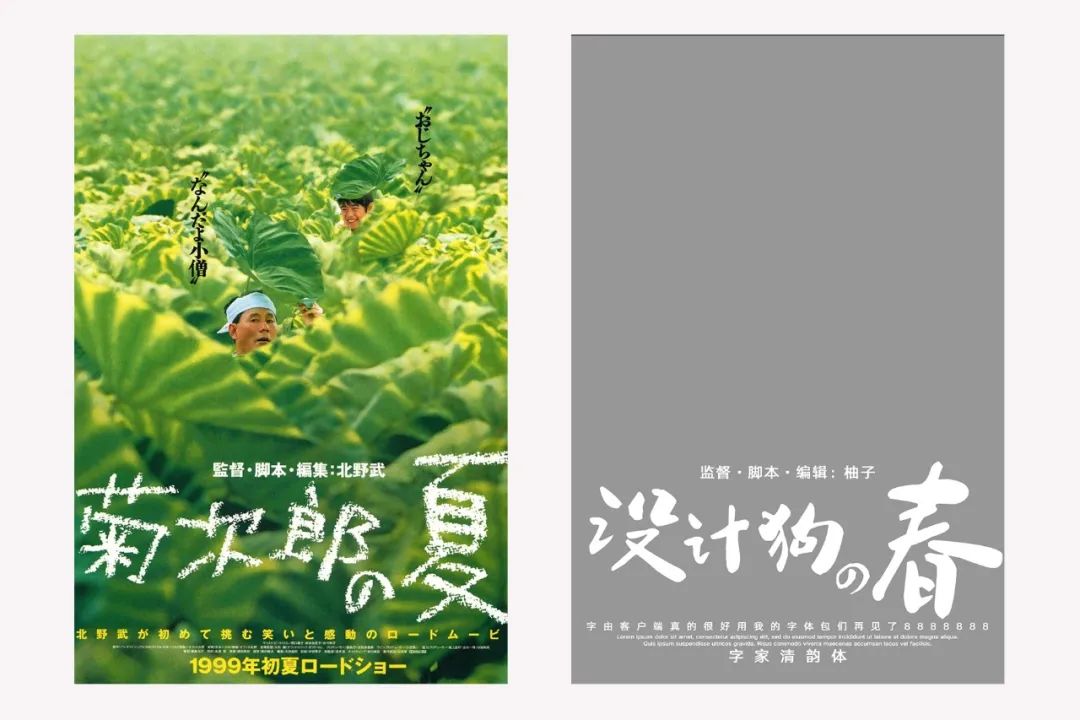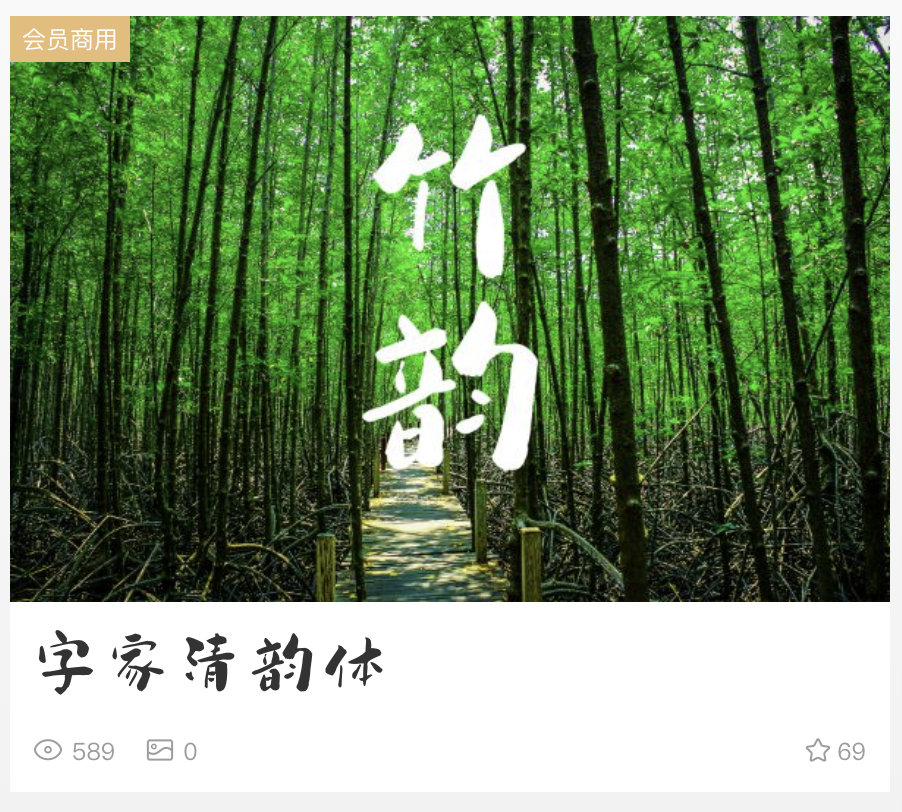
如何在朋友圈不动声色地“撩甲方”,这几招赶紧学起来~
🌱天气慢慢暖和起来了,小伙伴们准备好出游踏青了吗~出门踏青一定要多拍些美美的照片发朋友圈~
作为一名优秀的设计从业者,朋友圈的图片可是对你设计水平的肯定啊!要抓紧机会发财~
万一这样的朋友圈,被挑剔的甲方霸霸看到了,怎么能放心地把设计需求交给你呢?
想脱颖而出的诀窍就是模仿电影海报啊!文艺气质一下就上来了,甲方霸霸看过以后直呼内行!不信一起来试试?
《菊次郎的夏天》的海报可以说很经典了,模仿一下它的构图。
柚子选择了字家清韵体,有点日系的感觉了。
配上图以后一下就有了春天的活力感~成功!
《又见奈良》是一个比较小众的文艺片,海报的精髓就是左边的手写字体。
字体替换成汉呈疯狂行草试试,这款字体保留了手写体的随意洒脱感,非常适合做标题字。
替换背景图片立刻文艺感满满~
《少女集》的海报版式可以说很百搭了。同样是手写字的标题字,柚子选了点字逸致体,它很好地保留了手写字的笔触,很有装饰感。
这样的版式不用考虑标题字是否清晰的问题,不管什么样的图片都适用哦~
《小偷家族》相信大家都很熟悉了,因为我们是光荣的赶稿家族✌️
柚子一眼就看中了字家童颜体,完全是原版海报的中文版吧?稚嫩的笔划,非常有文艺海报常用字体的感觉了~